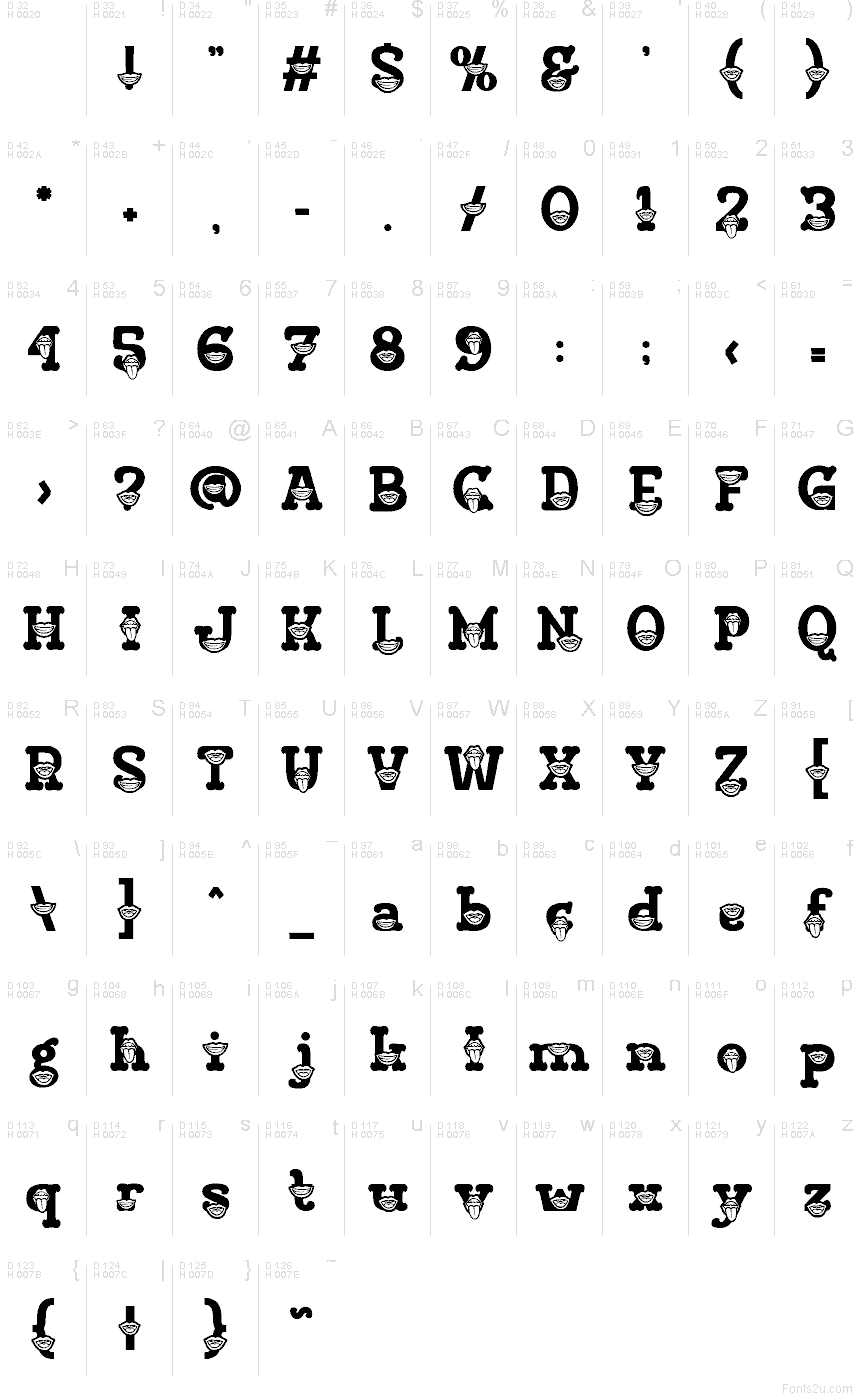
Visage Face Seven, eine kostenlose, von Lippen inspirierte Display-Schrift von Putracetol Studio, orientiert sich an der Pop-Art-Ästhetik: volle, schwarze Formen kombiniert mit kleinen Mund-Symbolen, die sich in die Buchstaben schmiegen. Das Alphabet wirkt frech und cartoonartig, mit weichen, kräftigen Kurven und wiederkehrenden Lippenmotiven, die das Design eher zu einem verspielten Grafikmuster als zu einer gewöhnlichen Schrift machen.
Diese kostenlose Schriftart eignet sich perfekt für Beauty-Branding, Club-Flyer, Albumcover, Poster-Überschriften und Social-Media-Titelbilder, bei denen die Buchstaben gleichzeitig als Text und Bild fungieren. Sie passt auch hervorragend zu Logos oder kurzen Namen auf Verpackungen – besonders, wenn ein Schriftzug flirty und auffällig wirken soll, ohne dass zusätzliche Illustrationen nötig sind.